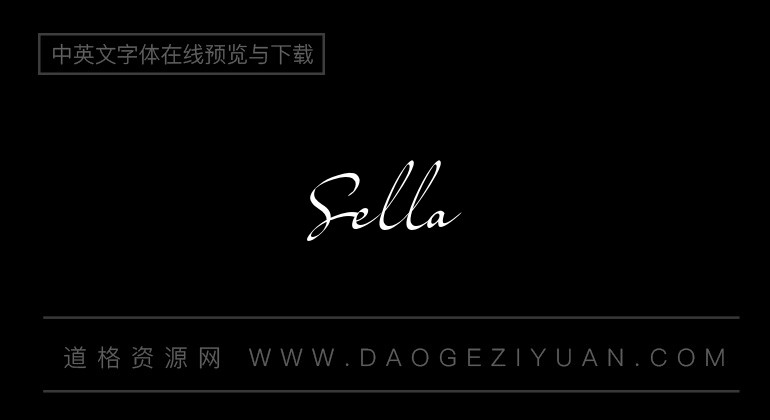
Sella
Sella 是一款极简风格的英文字体,由著名的西班牙设计师 Pablo Impallari 创作。它的特点是简洁、精致,在英文字体中拥有独特的气质。它的字体设计原则是以简单、精致、清晰的线条为主,使字体更加飘逸,更有质感。Sella 字体适用于各种类型的设计,如报纸、杂志、海报、标志等,因其简洁、精致的特点,可以让您的设计更加精彩。
Sella是一款非常不错的手写艺术字体,具有很好的视觉感,适合于文化类的宣传设计、商业类品牌的广告和产品包装设计以及个性化文字排版等较多场景。